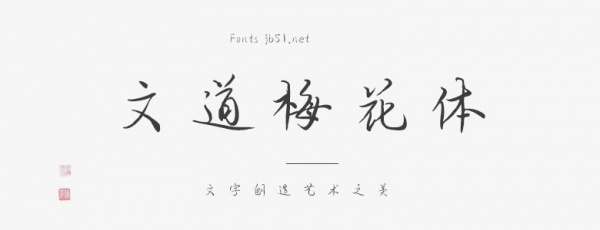
文道梅花體是一款獨(dú)特且富有藝術(shù)性的字體,它的設(shè)計(jì)靈感源于中國(guó)傳統(tǒng)書法的筆觸和線條,融合了現(xiàn)代字體設(shè)計(jì)的理念和技術(shù)。字體的線條流暢、優(yōu)雅,同時(shí)具有一定的力度和骨感,給人一種傳統(tǒng)與現(xiàn)代相融合的美感。 文道梅花體的字母形狀獨(dú)特,具有強(qiáng)烈的個(gè)性化特征。